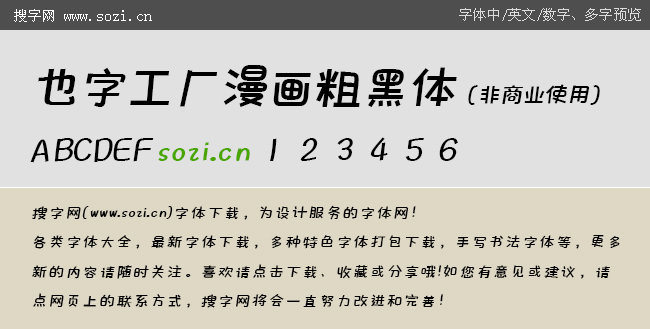
也字工廠漫畫粗黑體
搜字網(wǎng)給大家提供一款也字工廠漫畫粗黑體(非商業(yè)使用)中文字體下載,也字工廠漫畫粗黑體是一款卡通字體,字體以黑體做為基礎(chǔ)字體,筆畫富于變化,使字體看上去生動(dòng)有趣,字體錯(cuò)落有致,具有很好的視覺效果。適合應(yīng)用于兒童繪本、兒童海報(bào)、網(wǎng)頁設(shè)計(jì)等應(yīng)用(此字體為個(gè)人非商用版,商用可以聯(lián)系:官方網(wǎng)址:https://yefont.com/home,聯(lián)系方式:13798980448)。